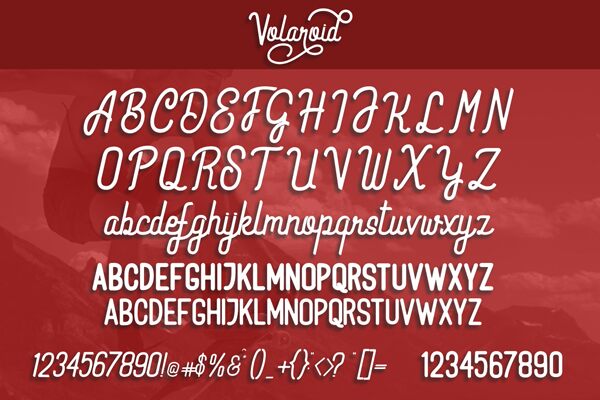
Przedstawiamy Volaroid font duo – prosty font łączący nowoczesny styl z estetyką vintage. Zapewnia to połączenie nowoczesnej i vintage atmosfery. Minimalistyczny design dla Twoich najlepszych projektów. Volaroid font najlepiej sprawdza się w logotypach, brandingu oraz nadrukach na koszulkach.